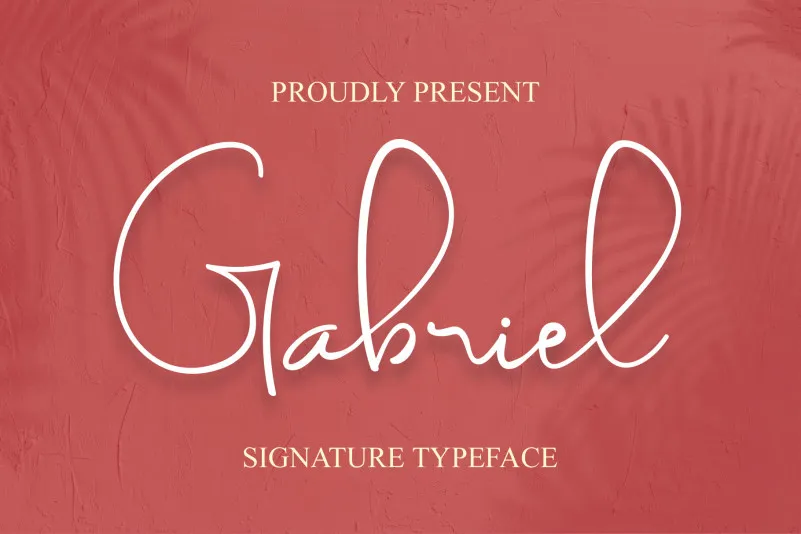
A fonte Gabriel Font é uma escolha fascinante para aqueles que buscam estilizar seus projetos com elegância e detalhes cuidadosamente elaborados. Esta font script se destaca como um complemento perfeito para seu acervo de fontes, oferecendo ao usuário a oportunidade de adicionar um toque único e sofisticado em qualquer projeto impresso ou digital. A Gabriela Font é particularmente adequada para textos legíveis e detalhados que exigem uma sensação única e personalizada, tornando-a uma ótima opção para designers gráficos e criativos, que buscam um recurso de alta qualidade com qualidades distintivas e versáteis. Com seu design meticulosamente cuidado, a font Gabriel é perfeita para incorporar em qualquer projeto da sua biblioteca de fontes, tornando-o uma escolha inteligente para quem busca trazer mais vida e personalidade às suas criações.